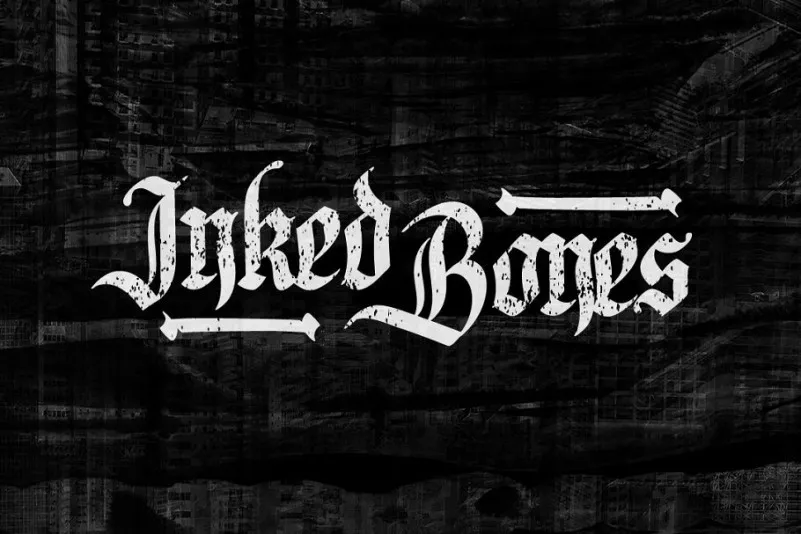
Inked Bones Blackletter Font – Download Grátis
Ink Bones Blackletter Font é uma tipografia geométrica moderna do tipo blackletter que traz à tona elementos arquitetônicos e elegantes. Desenvolvida por Måns Grebäck durante 2019, essa fonte exibe um aspecto de arte manual, característica de seu estilo blackletter autêntico. É perfeitamente adaptável tanto para cenários medievais quanto para o uso moderno de tipografia gótica. A sua geometrização a torna ideal para diversos aplicativos visuais como graficos tatuados, textos em citações da cultura medieval, capas de livros, design de camisetas, logotipos, panfletos, spots de filmes e banners. É uma escolha perfeita para aqueles que procuram adicionar um toque único a qualquer projeto. Ink Bones Blackletter Font é projetada para permitir à criatividade fluir livremente – seja em citações gráficas de tatuagens, capas de livros ou em aplicações digitais de texto breves. Com seus detalhes arquitetônicos e sua estrutura elegante, essa fonte traz um toque moderno a qualquer projeto que ela adorne.